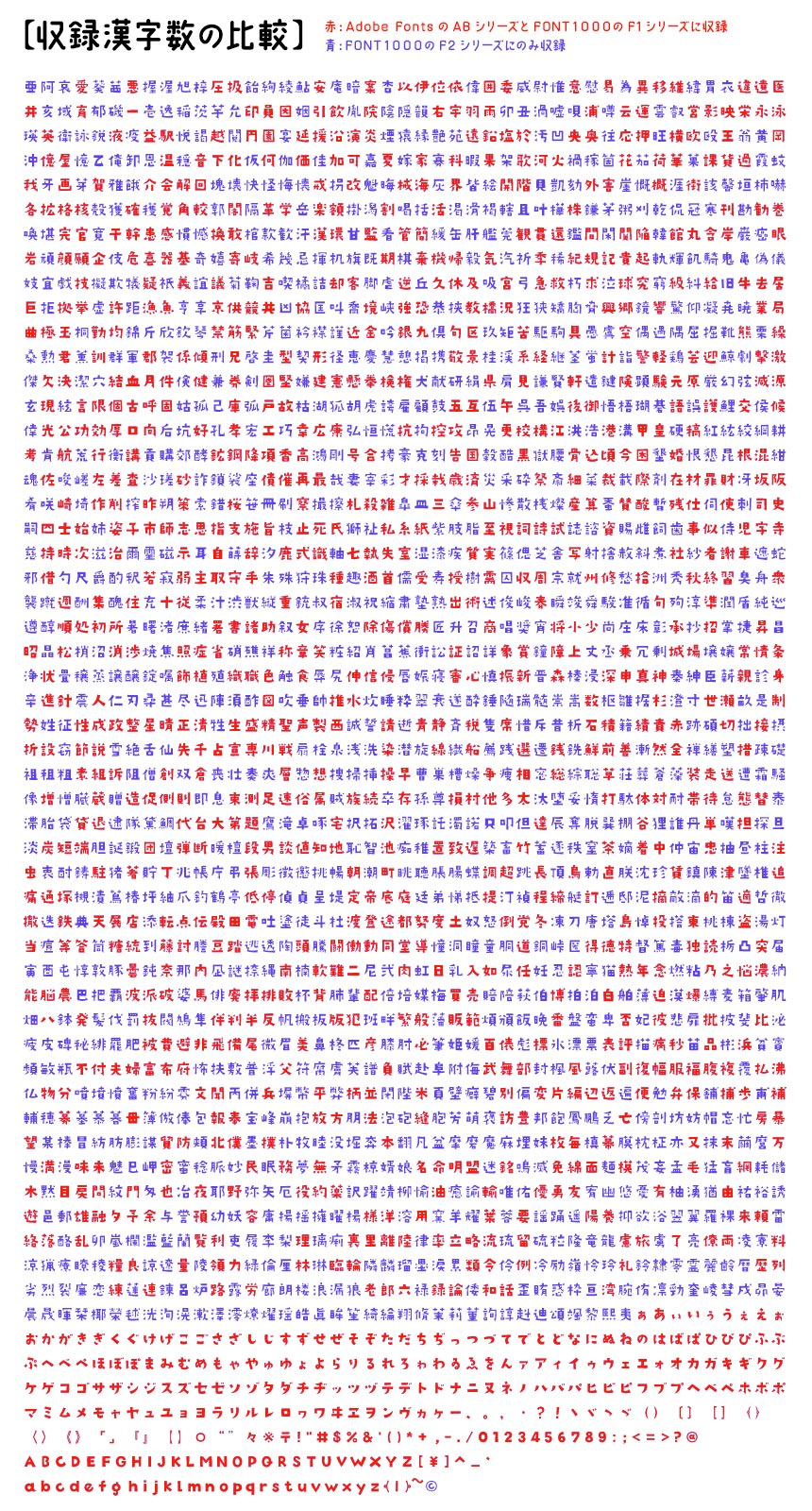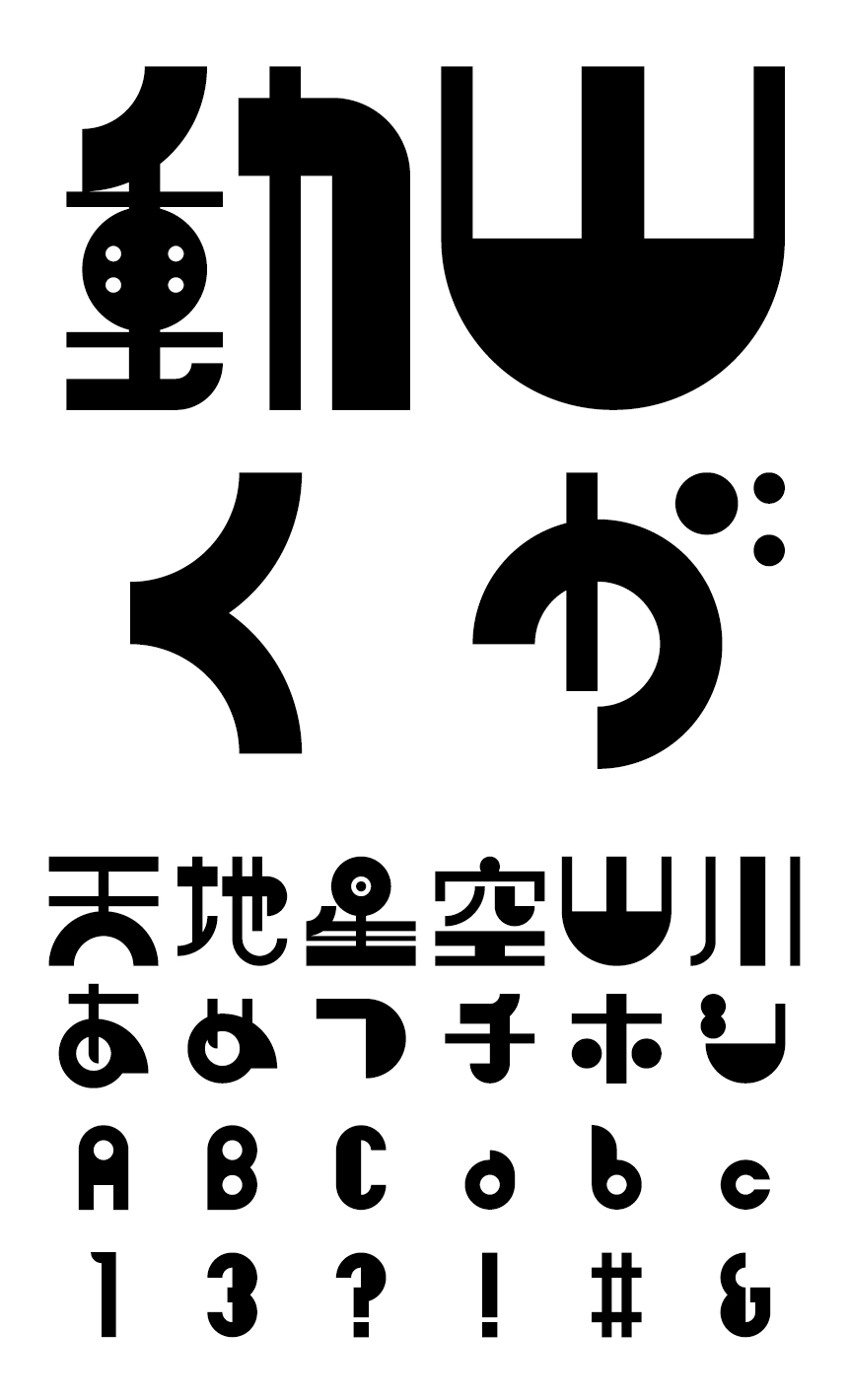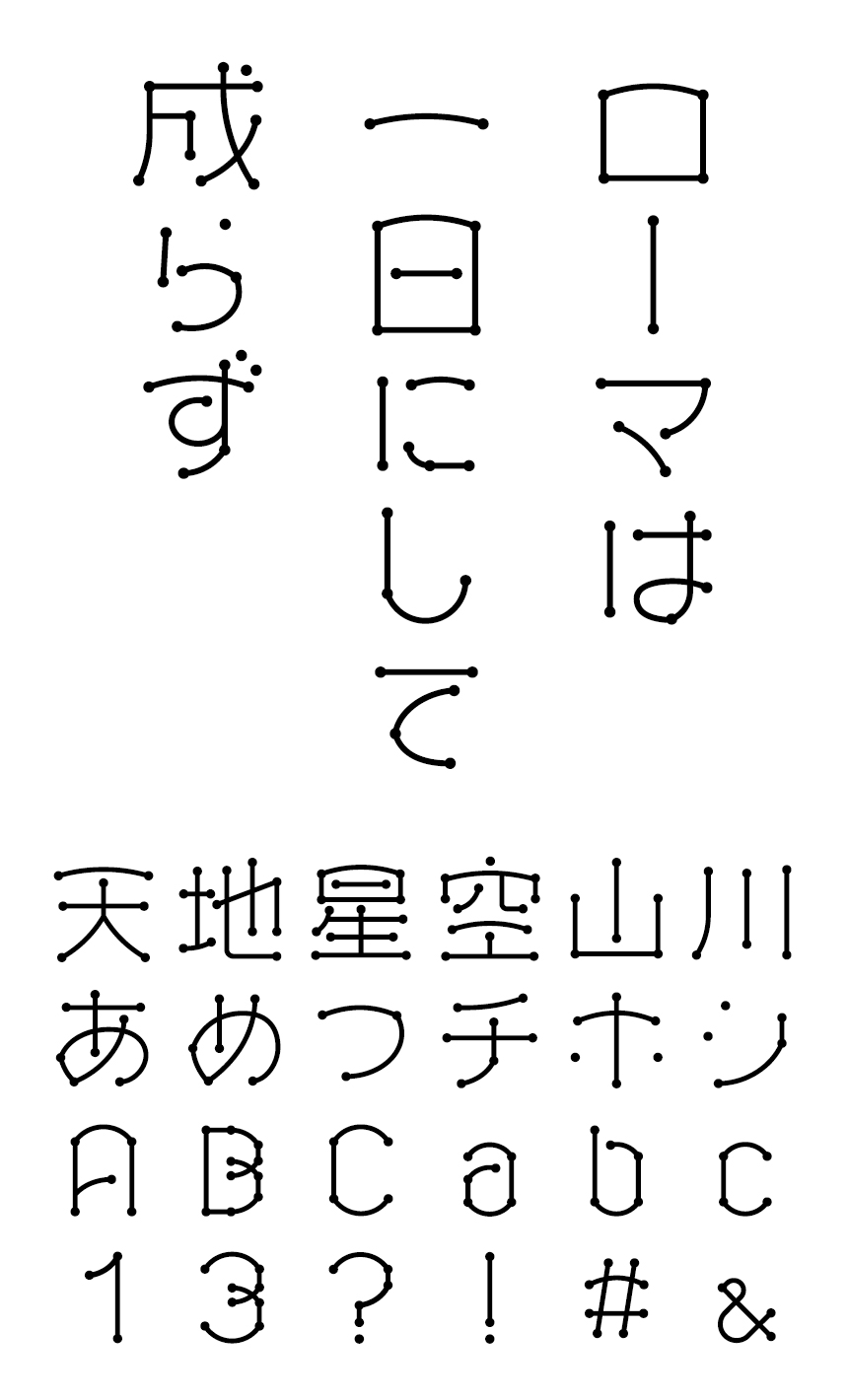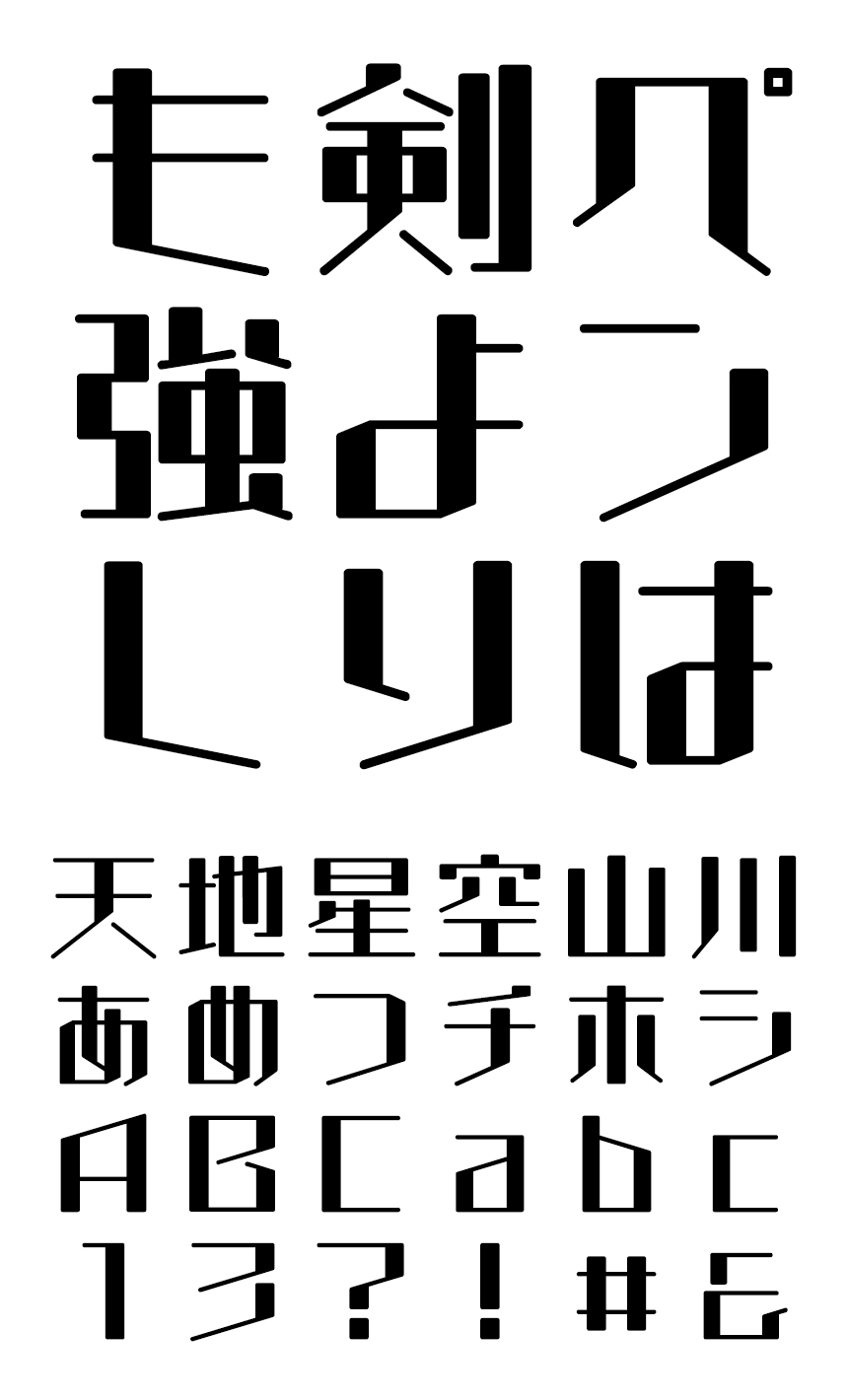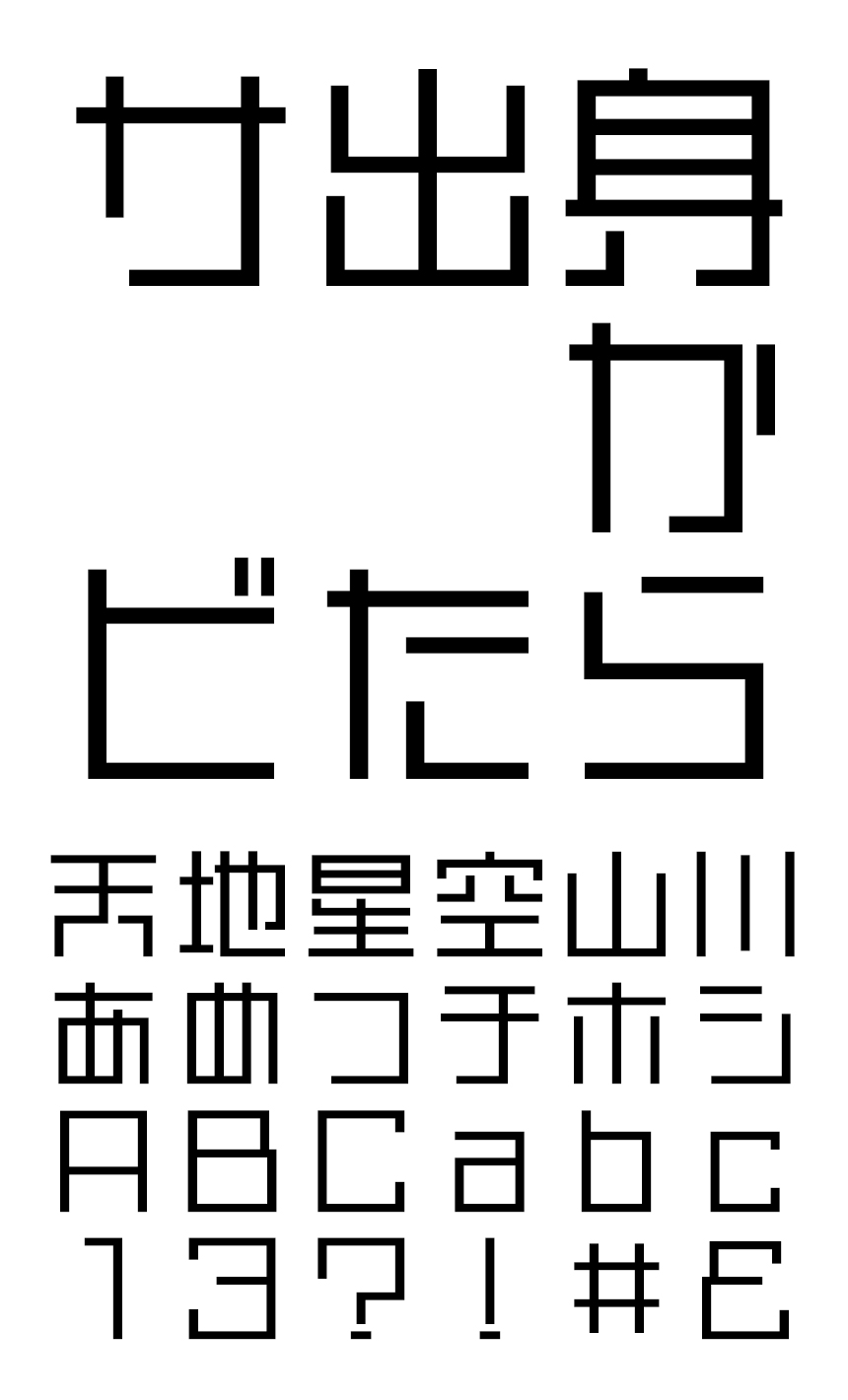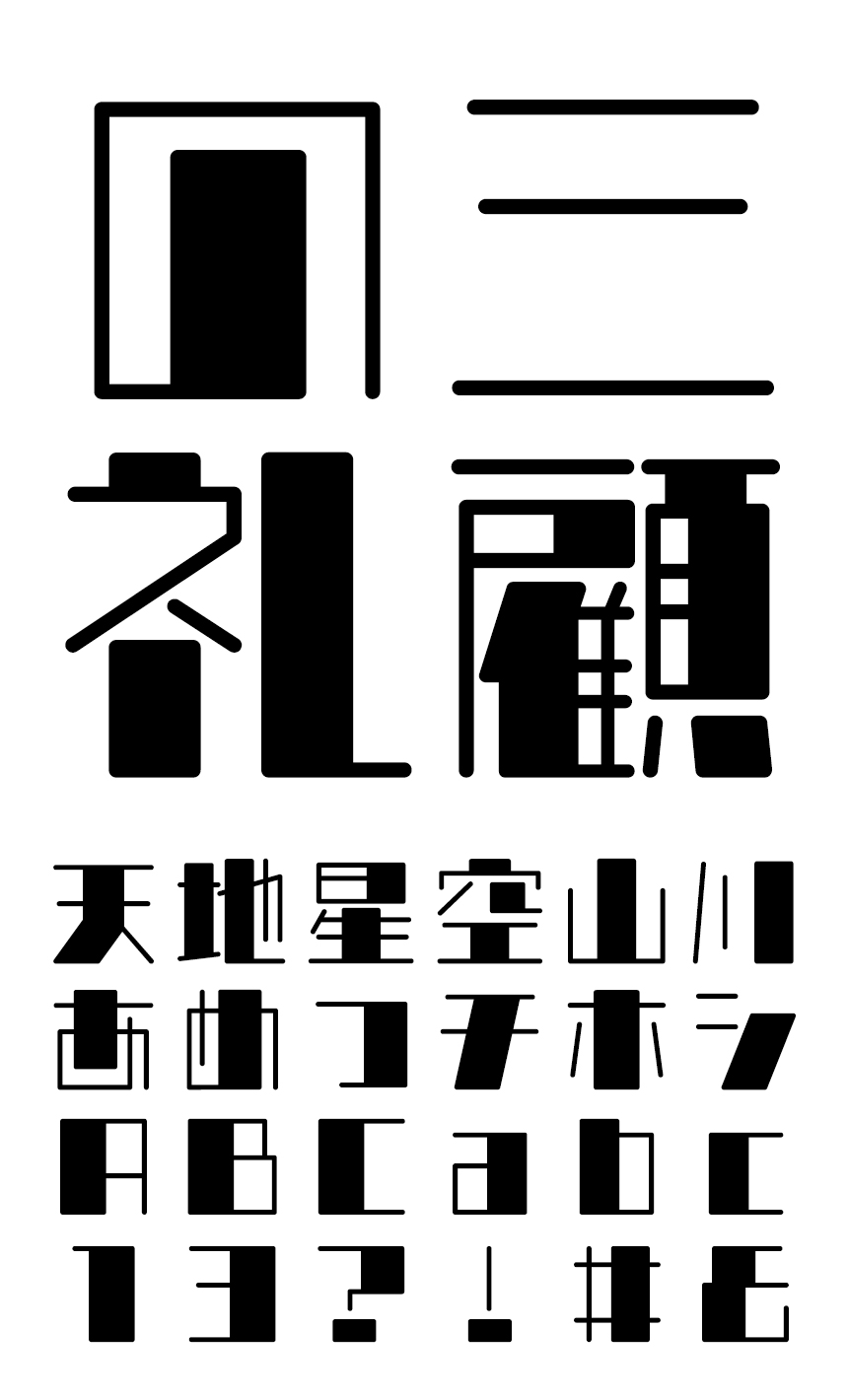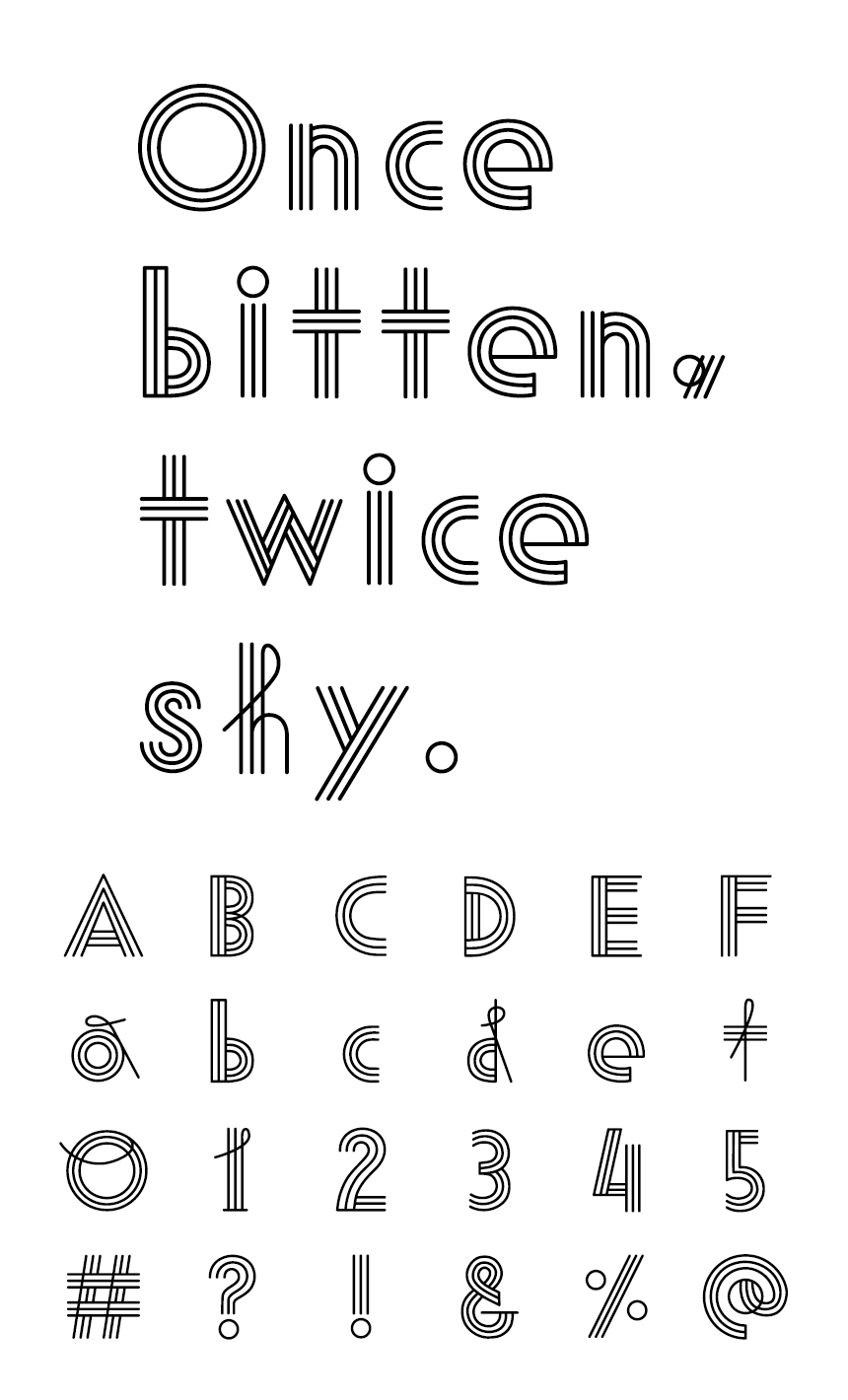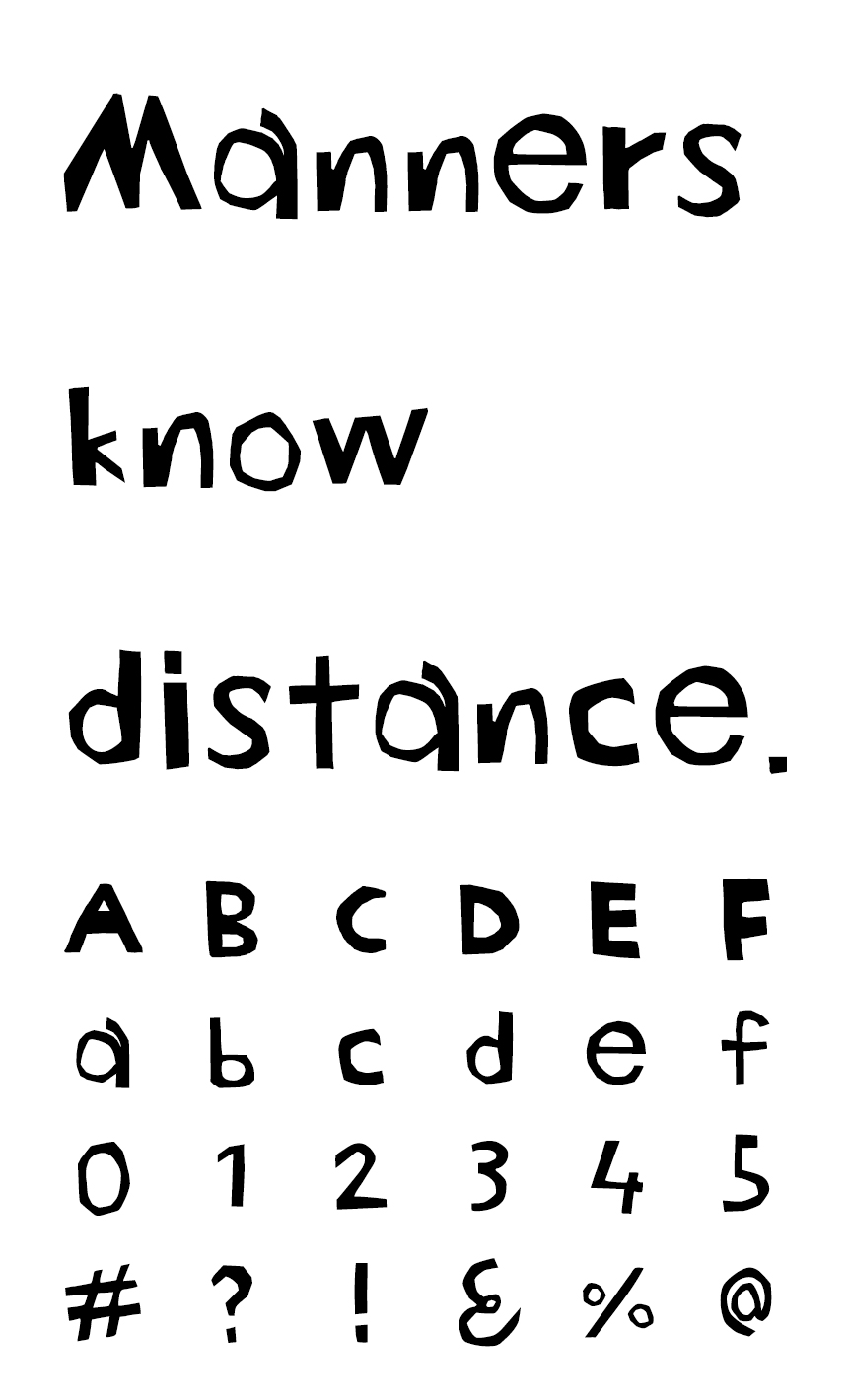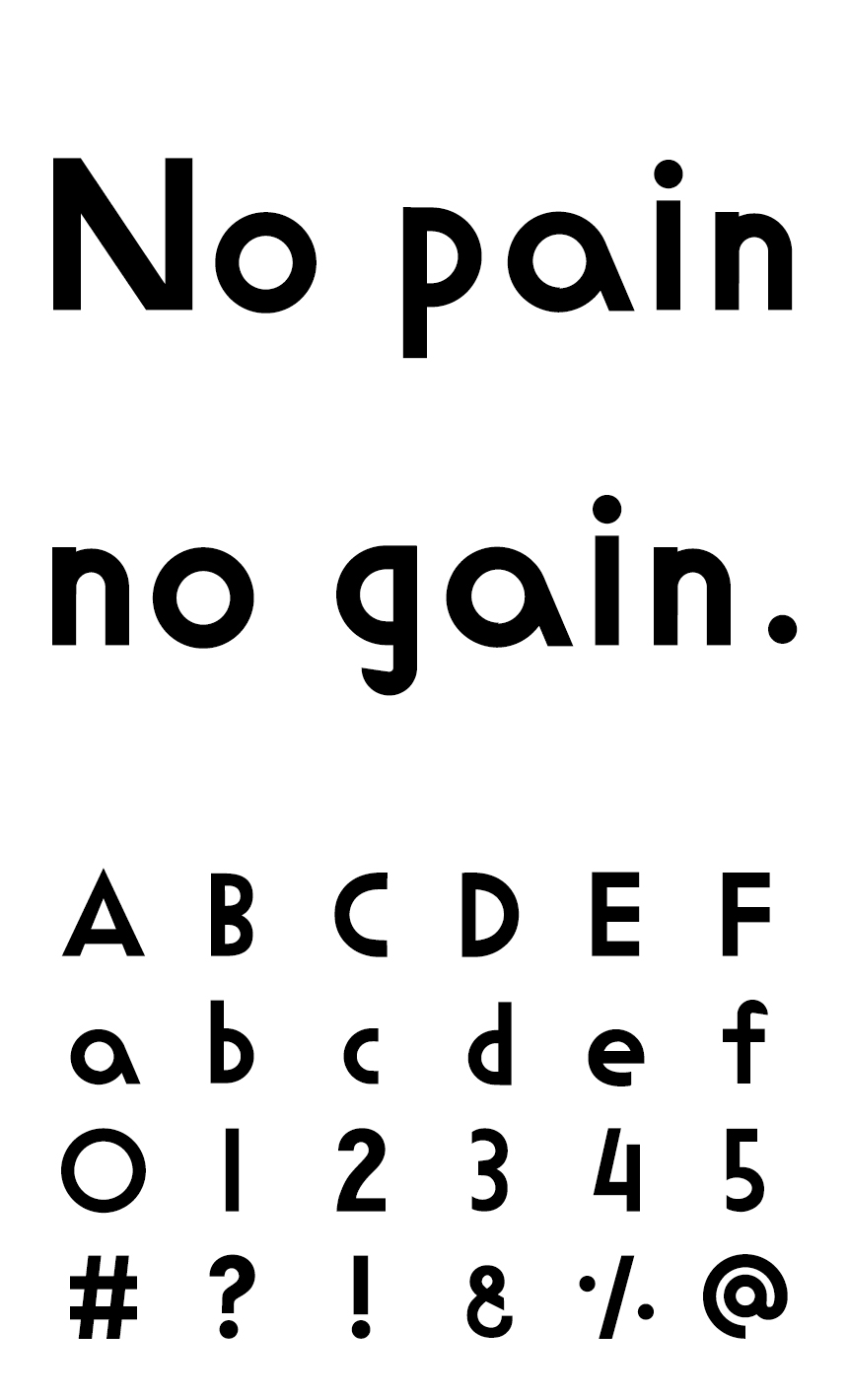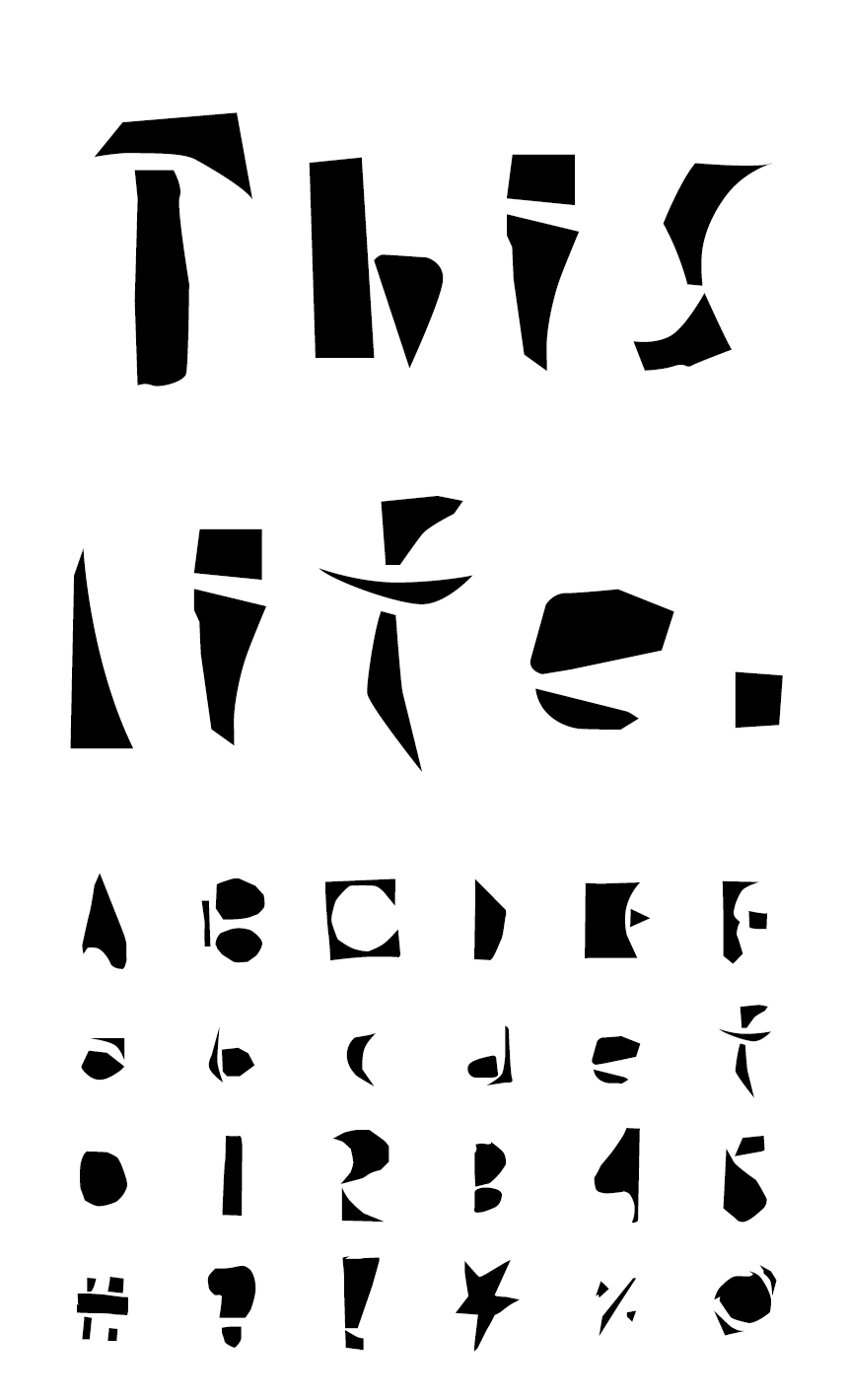
FONT1000 デザインフォント
日本語で文章を組むのに最低限必要な文字を選定、さまざまな和文フォント制作にチャレンジしようと設立されたフォントブランドFONT1000。キリギリスでお馴染みの七種泰史氏や味岡伸太郎氏、豊島晶氏など多くの参加デザイナーにより、グラフィックデザインに適した個性的で豊かなフォントを販売中です。
FONT1000とは
─── フォントの制作はJISの約7,000字が基準となっている。しかし、全てのフォントに本当にそれだけの字種が必要なのか。写植の時代にもそれよりはるかに少ない文字数で対応してきた筈ではないか。少ない文字数ですむのならばもっと多くのデザイナーがタイプフェイスのデザインに参加できる。そこから創意溢れるタイプフェイスが創作されることにならないか。
そんな素朴な思いからFONT1000の活動は始まりました。
当初は日本語の文章に最低限必要な文字として漢字1,000文字+両仮名と若干の約物が選定されましたが、現在ではさらに人名漢字などを加えた漢字2,286文字+両仮名と約物、そしてアルファベットの収録が基本となっています (※F1シリーズは旧仕様:漢字1,000文字+両仮名・約物198文字のまま) 。現在30名以上のデザイナーが参画、個性あふれる137商品のラインナップです。
Adobe Fontsで提供されるFONT1000 ABシリーズとの違い
Adobe Fontsで提供されるFONT1000 ABシリーズの収録漢字が1,000文字なのに対し、デザインポケットで取り扱っているFONT1000 F2シリーズは約2.3倍となる約2,280文字と大幅に充実しています。
FONT1000 F1000シリーズとAdobe Fontsで提供されるFONT1000 ABシリーズとの違い
※1 Adobe Fontsで提供されるFONT1000 ABシリーズおよびデザインポケットで取り扱っているFONT1000 F1シリーズは、常用漢字ベスト1,000文字。
※2 デザインポケットで取り扱っているFONT1000 F2シリーズは、常用漢字ベスト1,000文字+人名漢字他 約1,280文字(各書体によって収録文字数が異なります)
FONT1000 F1000シリーズとAdobe Fontsで提供されるFONT1000 ABシリーズとの違い
上の画像で赤い文字は、ABシリーズ、F1シリーズ、F2シリーズに収録されている文字。青い文字は、F2シリーズにのみ収録されている文字です。Adobe Fontsで提供されているABシリーズでは収録漢字が半分以下となっています。